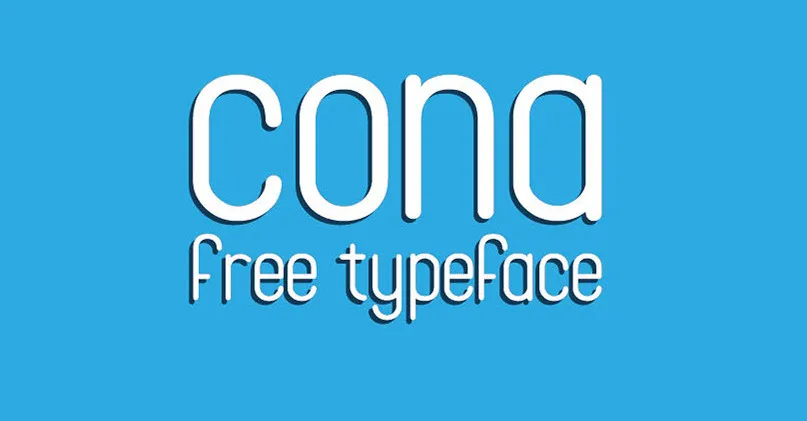
Cona Typeface é uma nova família de fontes góticas sem serif, criada pela designer Marta Coronado. Para aqueles que colecionam fontes, Cona oferece um desafio visual inovador e impressionante. Fornecida no formato OpenType, esta tipografia inclui diacritics para muitas línguas europeias. Cona é uma fonte de tipo gótico sem serif que mantém uma estrutura geométrica para melhor legibilidade, enquanto sua forma arredondada dá ao tipógrafo um caráter mais relaxado e amigável. Cona foi projetada especificamente para headlines e textos não-destacadoss, proporcionando um contraste harmonioso em qualquer projeto visual. Esta fonte é uma excelente adição para designers que estão sempre buscando novas opções de tipos para suas criações. Com sua simplicidade arredondada e estrutura geométrica, Cona oferece uma maneira elegante e moderna de destaque os títulos em seus trabalhos.